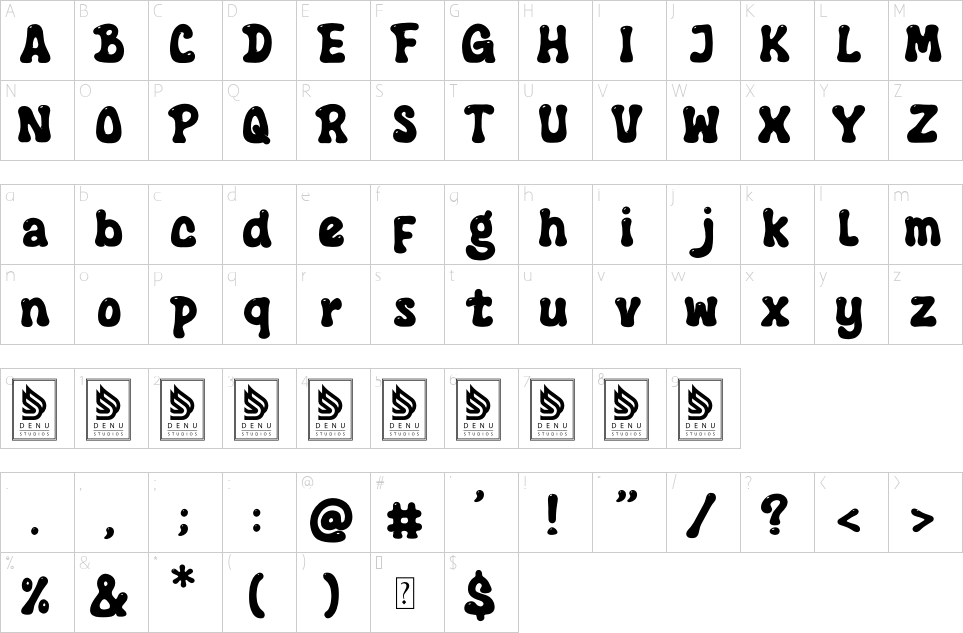
A fonte Poppy Boo é um charmoso complemento para projetos de design gráfico, oferecida de forma gratuita pelo site 1001 Free Fonts. Ela foi projetada pela Denustudios, e já foi baixada cerca de 735 vezes. Com um design levemente desenho infantil e uma infusão de cor, a Poppy Boo é uma escolha ideal para aqueles que buscam uma fonte que brinque com a leitura e o entendimento de texto. Seja para criar um layout amigável e agradável ou para dar um toque único em uma página web, esta fonte adicionará um toque especial a qualquer projeto. E para aqueles que querem incorporar esta fonte sem comprometer suas finanças, o download gratuito do Poppy Boo é um excelente recurso.